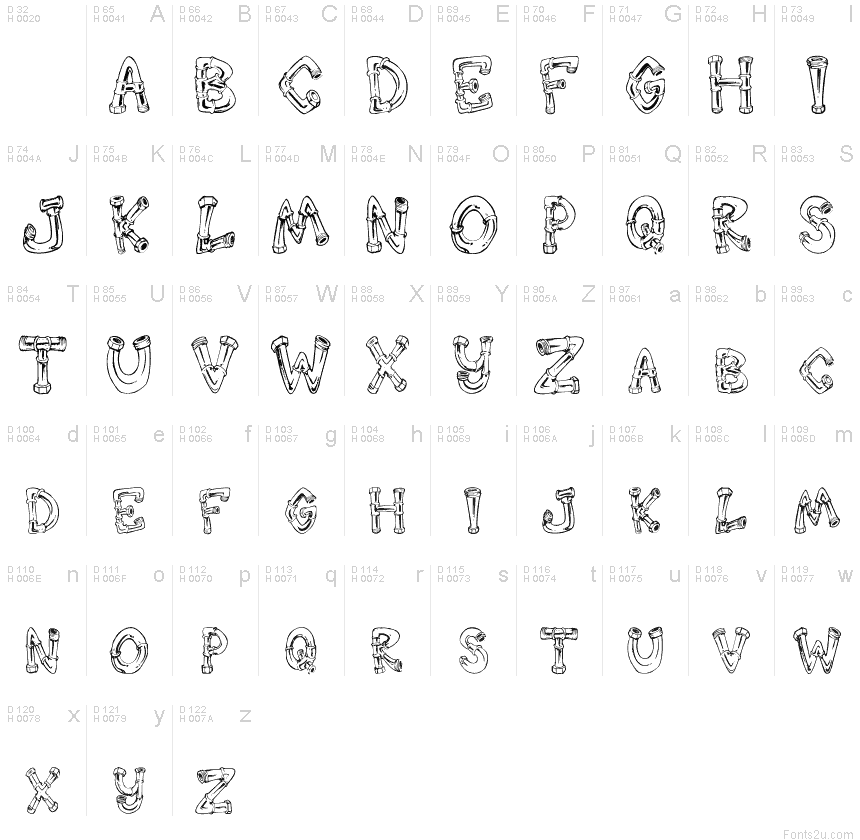
Down the Drain di Melle DERIEPPE Claude è un font display in stile cartoon gratuito che sembra colare direttamente dalla pagina. Ogni lettera sembra un tubo traballante intasato di melma, con contorni schizzati e tasche gommose che le conferiscono un fascino disordinato e disegnato a mano. Ha una struttura leggera e ariosa nonostante il carattere grunge, così i tuoi titoli rimangono leggibili pur risultando umidi, bizzarri e meravigliosamente ripugnanti.
Con Down the Drain, puoi puntare su tutto ciò che è appiccicoso, spettrale o a tema fognario: poster di Halloween, progetti scientifici per bambini, inviti a feste slime, titoli di fumetti disordinati, packaging disgustosi o stravaganti miniature di YouTube. Questo font gratuito rende al meglio in grande e in grassetto, dove tutte le gocce e le pozzanghere possono respirare. Prova ad abbinarlo a un font senza grazie pulito e neutro per il corpo del testo, per contenere il caos e mantenere il messaggio chiaro.